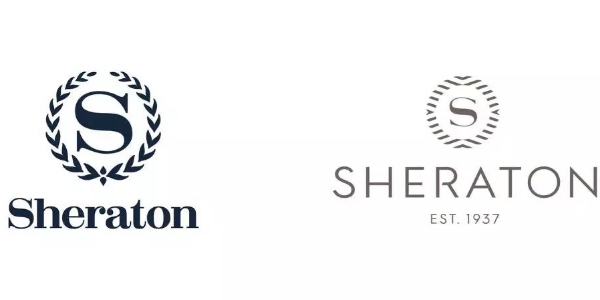
喜来登推出新LOGO,标志性桂冠更时尚!
喜来登酒店创办于1937年,是万豪国际集团旗下最重要的酒店品牌。喜来登在全球70多个国家和地区近450家酒店,可以让客人可以轻松探索、放松并享受洲际旅行。
喜来登通过创新的客户体验、差异化设计、多渠道营销及对专注的服务来提升品牌价值。
3月11日,富有开拓性传统的喜来登推出了一个新标志,在向过去致敬的同时,也描绘了品牌的整体愿景:让喜来登成为世界各地社区的中心聚集地,欢迎客人和本地人进入喜来登现代化的城市公共空间。
“标志的演变反映了我们对业主和客人激越的能量和坚定的承诺,这不仅仅是一个标志,这是喜来登对我们创新客户体验愿景的象征性陈述,”全球品牌营销副总裁Mara Hannula说。
“这次重新设计的难点在于,这个新标志在保持旧标志的均衡性和认识度的同时,传递了现代化的外观和感觉,从而与重新设想的空间相匹配。”
作为进入中国的第一个西方品牌,以及第一个在东欧和俄罗斯开展业务的美国品牌,喜来登的标志性桂冠是世界上最知名的品牌标志之一。
作为品牌悠久历史的记号,标志性的喜来登“S”仍然位于新标志的中心。桂冠图形经过重新设计,四周的线条指向中间的“S”,代表着来自世界的运动和聚会的能量。